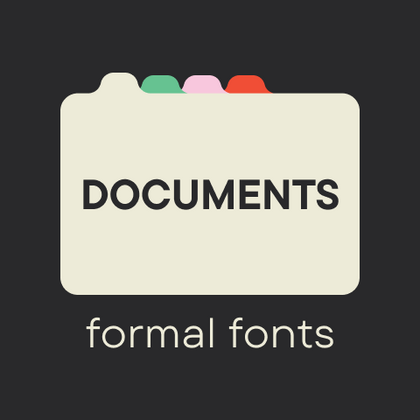
Формальные шрифты
Это гарнитуры, созданные для профессионального использования в деловой и официальной среде. Формальные шрифты сочетают сдержанный дизайн с четкими линиями, нейтральным характером и безупречную читаемость в любых форматах. В коллекции TypeType представлены как классические антиквы с умеренными засечками для корпоративной документации, так и современные гротески для цифровых коммуникаций — все они соответствуют строгим стандартам официальной типографики.
TT Commons™ Pro — TT Коммонс Про
«TT Commons» является зарегистрированным товарным знаком. «Pro» произносится как «про», и является разговорным сокращением слова «профессиональный».
TT Hoves Pro — ТТ Ховс Про
Произносится «ТТ Ховс Про». «Hoves» — производное слово от horizontal (с английского «горизонтальный») и vertical (с английского «вертикальный»). «Pro» произносится как «про», и является разговорным сокращением слова «профессиональный». Буквы «TT» являются аббревиатурой названия компании.
TT Norms® Pro Serif — TT Нормс Про Сериф
«TT Norms» является зарегистрированным товарным знаком. «Pro» произносится как «про», и является разговорным сокращением слова профессиональный. «Serif» произносится как «сериф», в переводе с английского «антиква».
TT Odellia — ТТ Оделлия
Произносится «ТТ Оделлия». Слово «Odellia» — производное от имён Одетта и Одиллия из балета «Лебединое озеро». Буквы TT являются аббревиатурой названия компании.
TT Odellia — старостильная антиква с современным рисунком, вдохновлённая венецианскими шрифтами и классической музыкой.
TT Neoris Pro — ТТ Неорис
Произносится «ТТ Неорис». «Neoris» — производное слово от neo («новый» с латинского) и rise («восход» с английского). Буквы «TT» являются аббревиатурой названия компании.
TT Supermolot Neue — ТТ Супермолот Нью
Произносится «ТТ Супермолот Нью». «Supermolot» — производное слово от super (с английского «супер») и molot (транслитерация слова «молот»). «Neue» — в переводе c немецкого «новый». Буквы «TT» являются аббревиатурой названия компании.
TT Supermolot Neue — технологичный модульный гротеск с футуристическим настроением и мощным функционалом. Яркость его характера сочетается с универсальностью применения.
TT Rationalist — ТТ Рационалист
Произносится «ТТ Рационалист». «Rationalist» — в переводе с английского «рационалист». Буквы «TT» являются аббревиатурой названия компании.
TT Rationalist — функциональный и оригинальный брусковый шрифт с актуальным рисунком. Он универсален и подходит как для заголовков, так и для массивов текста.
TT Bluescreens Pro — ТТ Блюскринс Про
Произносится «ТТ Блюскринс Про». «Bluescreens» — производное слово от двух слов blue (с английского «синий») и screen (с английского «экран»). «Pro» произносится как «про», и является разговорным сокращением слова «профессиональный». Буквы «TT» являются аббревиатурой названия компании.
TT Regins — ТТ Реджинс
Произносится «ТТ Реджинс». «Regins» — производное слово от reign, в переводе с английского «царствовать». Буквы «TT» являются аббревиатурой названия компании
TT Regins — шотландская новостильная антиква с королевским характером. Яркий контраст и острые треугольные засечки придают этому шрифту строгий и властный нрав.
TT Quaris — ТТ Кварис
Произносится «ТТ Кварис». «Quaris» — искусственно образованное слово от латинского «quartz» (кварц), и своим названием намекает на драгоценные камни. Буквы «TT» являются аббревиатурой названия компании.
TT Octas — ТТ Октас
Произносится «ТТ Октас». «Octas» — производное слово от octa, в переводе с греческого «восемь». Буквы «TT» являются аббревиатурой названия компании.
TT Octas — шрифтовое семейство с узкими пропорциями, построенное по принципу октагональности, в данной гарнитуре все окружности представляют из себя восьмигранники. Благодаря небольшим засечкам Октас приобретает насыщенный и старинный характер.